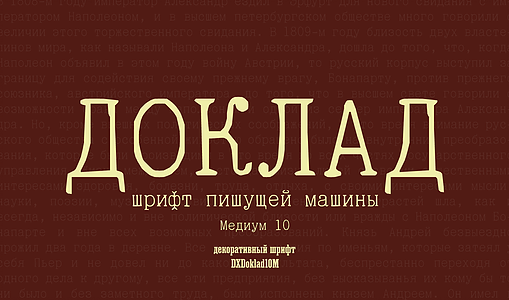
Мы продолжаем серию статей о шрифтовой истории и классификации и, наконец, переходим к новой группе шрифтов — брусковым. Хотя сейчас брусковые шрифты можно назвать универсальными и их часто используют для длинного текста, их история началась в первой трети XIX века с рекламы — это были очень крупные и яркие шрифты для привлечения внимания.
Брусковые шрифты — это шрифты с засечками, но без контраста: горизонтальные и вертикальные штрихи в них примерно одной толщины. Первые брусковые шрифты появились в Англии в начале XIX века. Это были жирные выразительные шрифты, их использовали в рекламе для привлечения внимания. Сейчас брусковые шрифты можно назвать универсальными, среди них много текстовых.
Брусковые шрифты можно разделить на группы в зависимости от формы букв.
Брусковые антиквы (Egyptian)
Время появления: начало XIX века
В двух словах:
Брусковые антиквы — это шрифты, близкие по форме к антикве, но с уменьшенным контрастом. Примерно такими брусковые шрифты были в первые сто лет своего существования, то есть в XIX веке.
Египетский шрифт Роберта Торна, 1820История и теория:
Египетские шрифты — собирательное название ранних брусковых шрифтов. Первый известный египетский шрифт появился в 1815 г. в каталоге лондонского словолитчика Винсента Фиггинса. У египетских шрифтов почти нет контраста между горизонтальными и вертикальными штрихами. Пропорции прописных знаков равноширинные (т. е. нет большой разницы между узкими и широкими буквами), конструкция довольно симметричная, с вертикальной осью овалов. Засечки у брусковой антиквы мощные, прямоугольные, без скруглений.
Название связано с Египетским походом Наполеона Бонапарта (1799), в результате которого в Европе узнали о цивилизации Древнего Египта, а также с названием французского фрегата Egyptienne, захваченного англичанами в 1802 г. и привезенного в Лондон в качестве трофея. По легенде, в самом начале XIX века в Париже всё египетское стало ужасно модным, а всё модное, соответственно, пытались назвать египетским — не исключая и шрифты.
Иногда в отдельную подгруппу выделяют итальянские шрифты — брусковые шрифты с обратным контрастом.
Примеры цифровых шрифтов
XeniaSwordsmanLehmann EgyptianLiberteenLehmann Egyptian — реконструкция узкого брускового шрифта XIX века, сделанного в словолитне Осипа Лемана.
Liberteen — постмодернистская ироничная трактовка классических брусковых шрифтов второй половины XIX века, в частности, шрифта Кларендон.
BalticaOptimusПример текстового брускового шрифта — Baltica, кириллический шрифт первой половины XX века по мотивам шрифта Candida Якоба Эрбара.
Неожиданное наблюдение: шрифты старых пишущих машинок по конструкции тоже очень близки к антикве. Например, Optimus — светлый брусковый шрифт, а поскольку это оцифровка шрифта пишущей машинки, то он ещё и моноширинный.
Зачем нужны?
Брусковые шрифты с явными историческими корнями лучше всего работают в типографике в духе XIX века — как в прямой её имитации, так и в современном дизайне с лёгкими историческими отсылками.
Брусковые шрифты без выраженного характера хорошо читаются в длинном тексте (в том числе в вебе — из-за низкого контраста), а моноширинный брусковый шрифт — находка для современного ироничного дизайнера 🙂
Можно ли брусковыми шрифтами набирать текстовые блоки?
Дима! Брусковые шрифты и текстовые блоки — очень обобщённые понятия. Всё-таки основное отличие шрифтов — их предназначение: акцидентные или текстовые. Текстовые шрифты можно увеличить и получить заголовки и другую акциденцию, акцидентные шрифты нельзя уменьшить и использовать для набора сплошного текста. Брусковые, или египетские, шрифты — это общее название шрифтов с засечками прямоугольной формы. Брусковые шрифты появились в самом начале 19 века и сначала заняли нишу акцидентных шрифтов: ими набирались рекламы, плакаты, листовки. Примеры британской рекламы 19 века. Васианед Реклама 19 века — это такой типографический взрыв. Печатники и пуансонщики начали усиленно экспериментировать с шрифтовым наследием: увеличивать контраст до предела в дидо-подобных шрифтах, приделывать засечки причудливой формы, а то и убирать засечки вовсе. Примеры экспериментов с буквами, варианты форм засечек. Тал Сложно представить такие шрифты в меньших кеглях и в наборе сплошного текста. Однако в середине 19 века появляются шрифты с брусковыми засечками, которые используются и в текстовом наборе — например, в газетах. Самый известный пример — Кларендон. Кларендон в наборе шрифтового каталога. Автор шрифта Роберт Бесли в тексте обращается к нечестным конкурентам, которые воровали рисунок шрифта из-за его возрастающей популярности |
||||||||
Кларендон — тоже брусковый шрифт, однако засечки переходят в штрихи с небольшим скруглением. Шрифт быстро стал популярен, потому что хорошо пропечатывался даже на дешёвой бумаге и при плохой печати. По рисунку Кларендон похож на переходную антикву, которой добавили жирности и увеличили засечки. |
Скайлар Чалланд о шрифте «Кларендон» |
|||||||
Шрифты типа Кларендона — это известные гарнитуры «Скулбук», или «Школьная», «Академическая» и другие. Удобочитаемость у таких шрифтов несмотря на брусковые засечки высокая — например, Скулбук до сих пор используется в русской школьной литературе. Шрифт «Кларендон» в основном наборе учебника. Математика. 5 класс. Просвещение |
Некоторые брусковые шрифты специально разработаны для текстового набора, некоторые — исключительно акцидентные шрифты. Чтобы понять, какой шрифт для каких задач будет оптимальным, советую читать аннотации создателей шрифта.